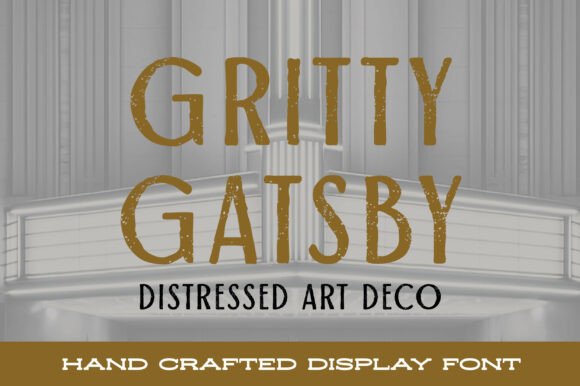
Gritty Gatsby
適切なデザイン要素を見つけるのは難しい場合がありますが、Gritty Gatsbyは作品を即座に引き立てる優れたコレクションを提供します。
POD(オンデマンド印刷)製品、結婚式の招待状、またはソーシャルメディアのグラフィックを作成している場合でも、Gritty Gatsbyは理想的です。